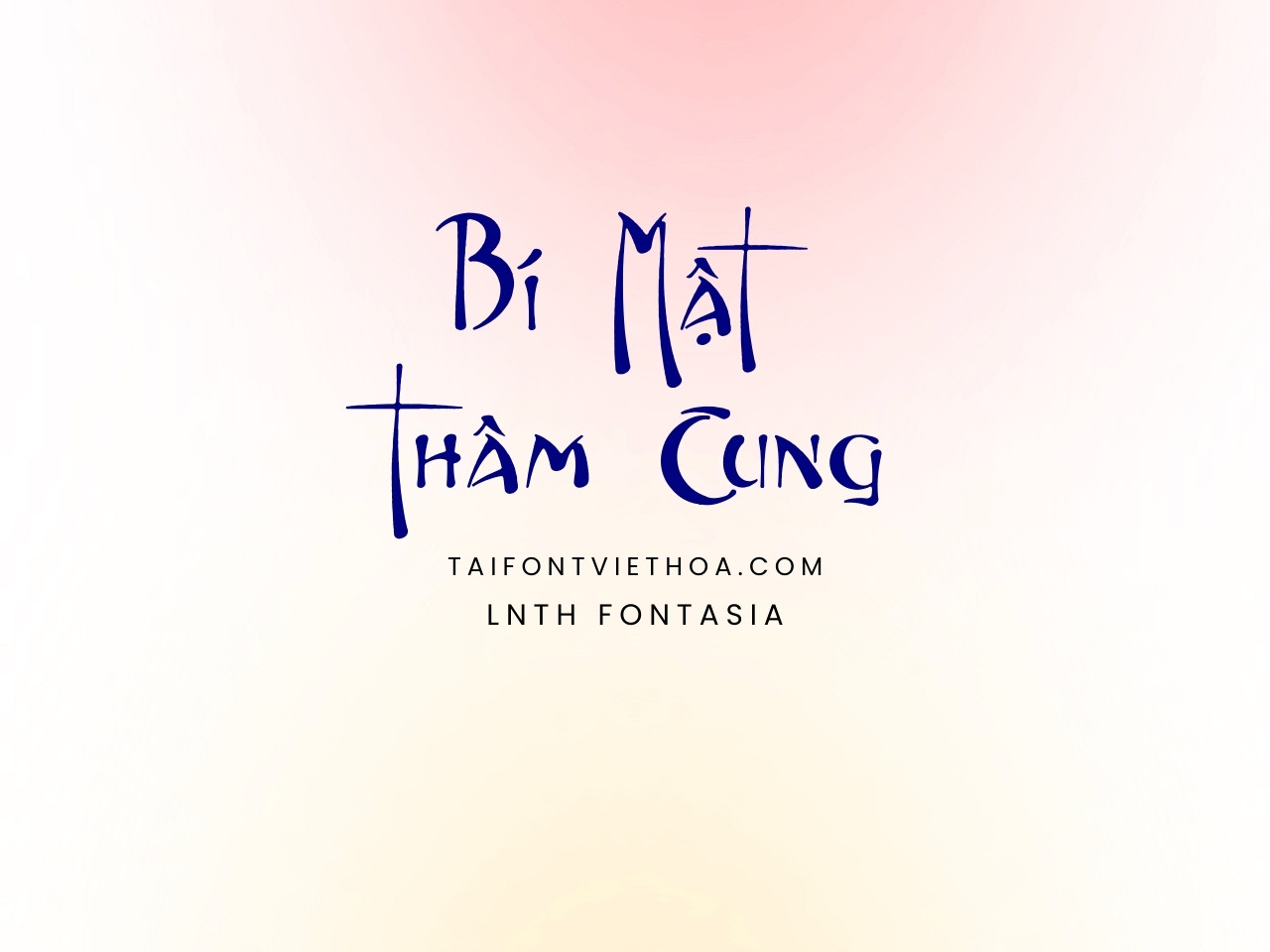
Font việt hóa LNTH Fontasia
Tác giả Font: Walter Velez
Giới thiệu về font LNTH Fontasia – Thư pháp giả tưởng mang hơi hướng huyền thoại
LNTH Fontasia là phiên bản Việt hóa từ font “Fontasia” – một kiểu chữ độc đáo được thiết kế bởi Walter Velez, lấy cảm hứng từ thư pháp phương Đông kết hợp với chất fantasy cổ tích phương Tây. Font mang đến cảm giác như đang bước vào thế giới giả tưởng, với các ký tự bay bổng, uốn lượn và đầy màu sắc cổ tích. Tuỳn Pucca là người thực hiện Việt hóa, giúp font hỗ trợ đầy đủ tiếng Việt và hơn 60 ngôn ngữ khác, mở rộng khả năng sử dụng trong các dự án đa ngôn ngữ hoặc toàn cầu.
Đặc điểm thiết kế và ứng dụng của LNTH Fontasia
LNTH Fontasia có thiết kế pha trộn giữa thư pháp và fantasy, với các nét chữ phức tạp, thanh mảnh nhưng vẫn đầy sự uyển chuyển và nghệ thuật. Font mang tính trình diễn mạnh, thích hợp dùng cho tiêu đề, trích dẫn sáng tạo, bìa sách hoặc đồ họa liên quan đến phim ảnh, trò chơi hoặc lễ hội. Các glyphs được cách điệu như ký hiệu phép thuật, tạo sự khác biệt rõ rệt so với các font thông thường.
Font phù hợp cho các ứng dụng như: poster lễ hội, banner phim hoạt hình, bìa sách kỳ ảo, truyền thông game, thiệp sinh nhật, sự kiện văn hóa hoặc thương hiệu cá nhân theo phong cách giả tưởng. Ngành nghề phù hợp: giải trí, nghệ thuật thị giác, truyền thông số, giáo dục sáng tạo hoặc thương hiệu cá tính mạnh.